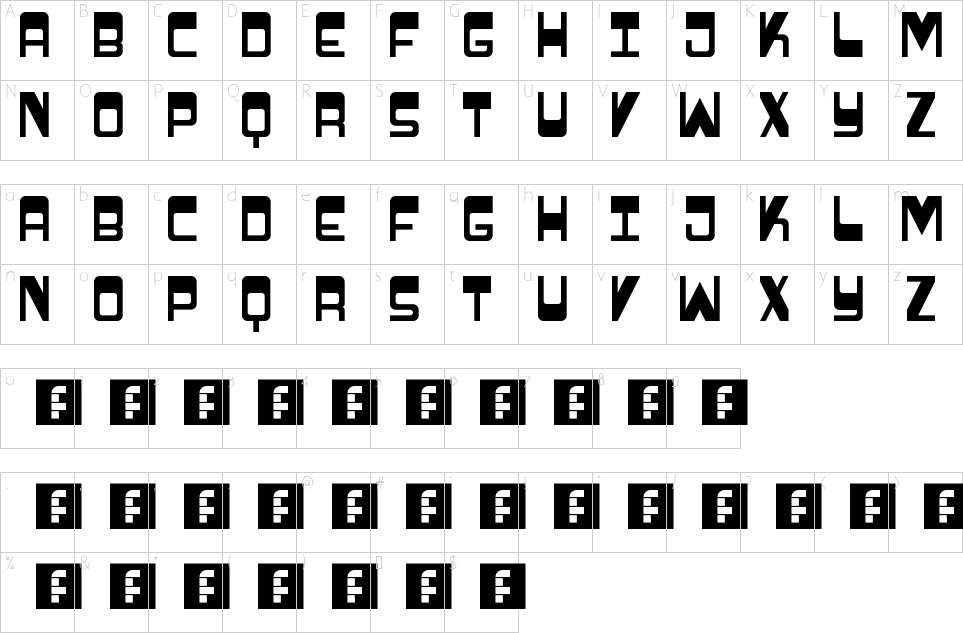
Aqui está uma descrição em português do Brasil, envolvente e natural, para a página de download da fonte ‘Psychedelic Font | 1001 Free Fonts’, seguindo as regras: Descubra a vibe deslumbrante da Psychedelic Font! Desenhada pelo talentoso Geronimo Fonts, esta fonte é perfeita para aqueles que querem enriquecer suas criações com um toque nostálgico e vibrante. Com um design que remete àqueles anos de loucura e otimismo, a Psychedelic Font transforma qualquer texto em uma pintura visual, criando uma atmosfera hipnótica e nostálgica. Esta fonte é uma ótima escolha para designers que procuram uma maneira única de dar vida aos seus projetos, tornando-os verdadeiros instantes de arte. Descubra por que esta fonte é tão popular, e baixe-a hoje! Com uma fácil instalação para Windows e Mac, ela é a escolha perfeita para quem busca estilos únicos para seus projetos.